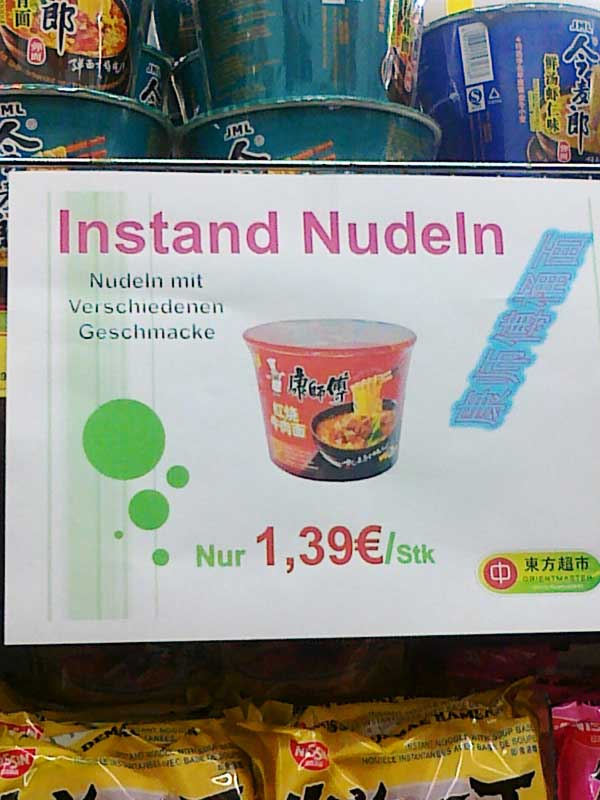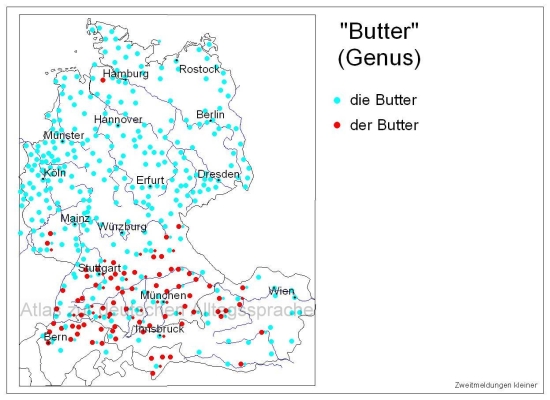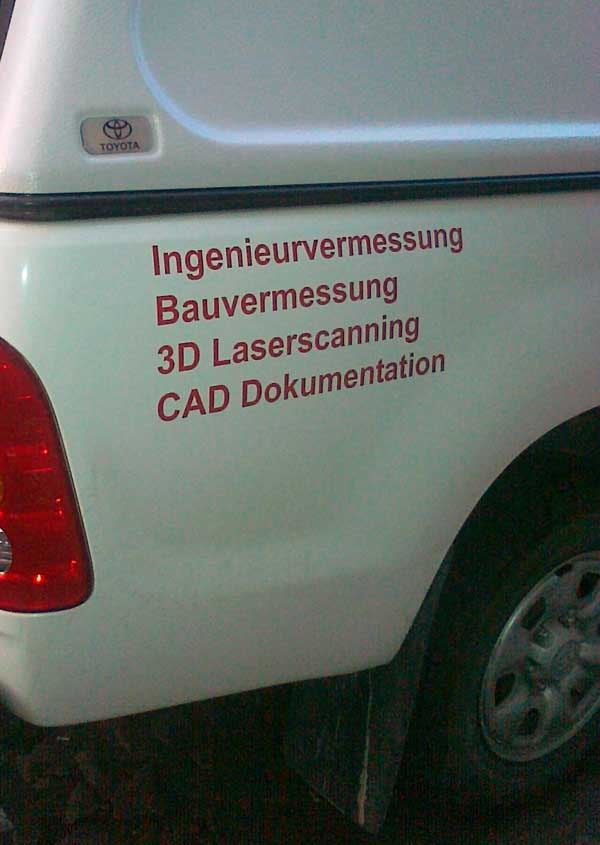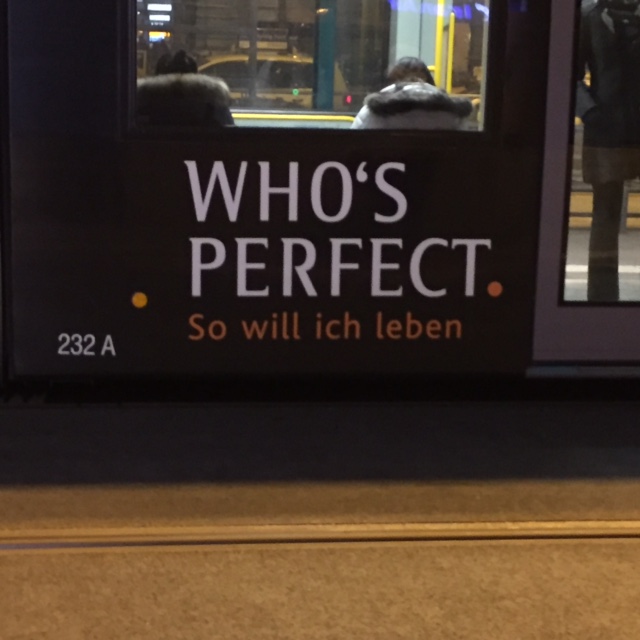
Nun ja, das gab es auch ohne Buchstabenklau.
Ich weiß nicht, ob hier jemand das Türkische restaurant "Lokma" im Schanzenviertel kennt. (ich glaube Susannenstraße). Neben dem Pamukkale schräg gegenüber gibts da den leckersten Döner den ich kenne - aber das wollte ich gar nicht erzählen, sondern, in den Räumlichkeiten war zuvor ein Edeka-Supermarkt, zu dem, so meine ich mich zu erinnern noch eine weitere Filiale in Ottensen gehörte, und das war die Firma
Fritz Fick
Vermessen hab ich mich schon selbst oft genug, auch ohne Ingenieur.
Diese Frage ist mir hier in Osnabrück neulich auch begegnet, änder das Ingenieur-Auto war zu schnell weg für ein Foto ...
Verfall- sondern in Minuskelziffern
So … wer findet jetzt das schönste Bild mit Verfallziffern? :hammer:
Ich glaube, dass das in genau diesem Logo beabsichtigt ist.
Dafür, dass es leider auch viele Gestalter gibt, die nicht wissen, wie ein korrektes Apostroph aussieht, denke ich, dass es für die Allgemeinheit dann doch zu subtil wäre.
Ja, das Problem ist zu speziell. Wäre schon interessant, was wirklich dahintersteckt.
Dafür, dass es leider auch viele Gestalter gibt, die nicht wissen, wie ein korrektes Apostroph aussieht …
Eigentor  :rockon:
Ich geb es zu – das passiert mir leider gerne.
Oder ist das vielleicht auch meiner schwäbischen Herkunft geschuldet?
Ich bin ja auch mit „der Butter“ aufgewachsen …
Ehrlich? Der Butter? Spannend!  :-D
Der rote Punkt bei Hamburg ist ganz sicher durch ausgewanderte Bayern zu begründen.
Das Thema Artikel ist immer wieder verblüffend! Lässt der Duden da eigentlich auch mal Variationen zu oder gibt es aus amtlicher Sicht immer nur einen fest definierten Artikel?
Spontan fallen mir noch ein: das/der Kaugummi/Radiergummi, der/das Essig, der/die Joghurt (das »die« habe ich aber in diesem Zusammenhang nur einmal gehört), der/das Draht.
Nutella ist natürlich der/die/das Beste ...!
Spontan:
der/das Bonbon
der/das Sechserpack
die/das Maß (Bier)
der/das Moment
die/das E-Mail
der/das Teil